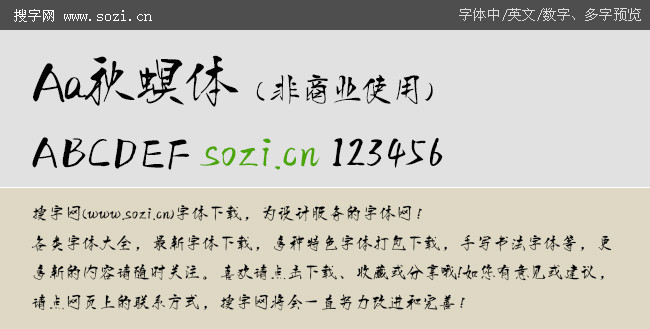
Aa秋螟體
搜字網(wǎng)給大家提供一款A(yù)a秋螟體(非商業(yè)使用)中文字體下載,該字體是一款漂亮的手寫書法字體,字體書寫時粗時細,書寫流暢,給人一種非常舒服的視覺感受,適用于平面宣傳設(shè)計、網(wǎng)頁設(shè)計、海報設(shè)計等應(yīng)用(此字體為個人非商用版,商用可以聯(lián)系QQ:1006760504)。